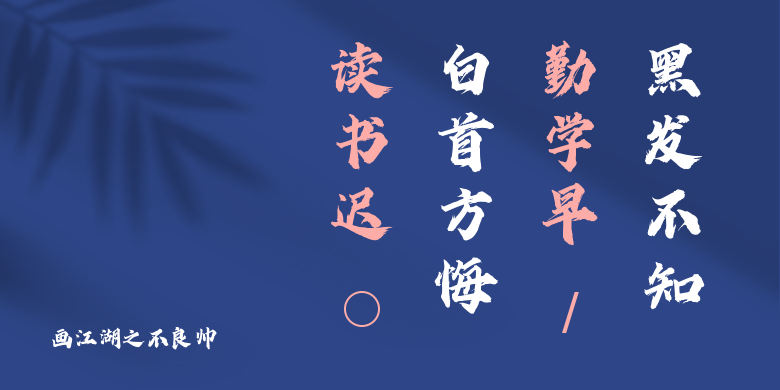
画江湖之不良帅
画江湖之不良帅,这款字体结构工整、笔画清晰,兼顾美观与易读性,适用于标题、正文、海报、包装、LOGO 等多种场景。字形优雅稳定,风格百搭耐看,适配日常排版与创意设计,让文字呈现更舒适、更具质感。画江湖之不良帅一笔一画,皆是细节,以均衡的比例、流畅的线条打造舒适视觉体验,字形端正大气,风格简约现代。无论是商业设计、品牌宣传还是日常排版,都能轻松驾驭,让文字更有格调与力量。画江湖之不良帅字体下载。